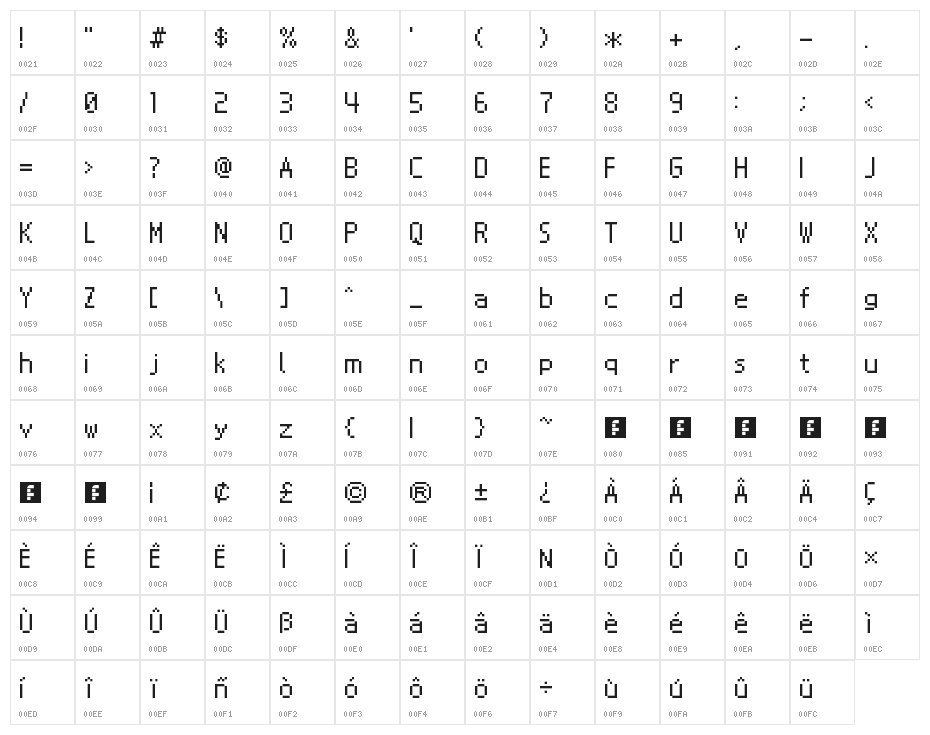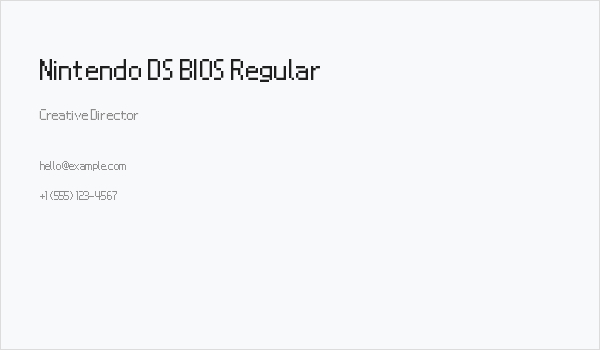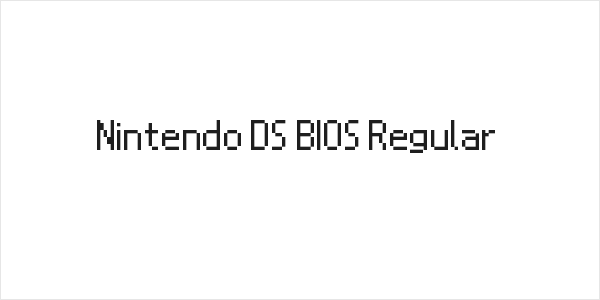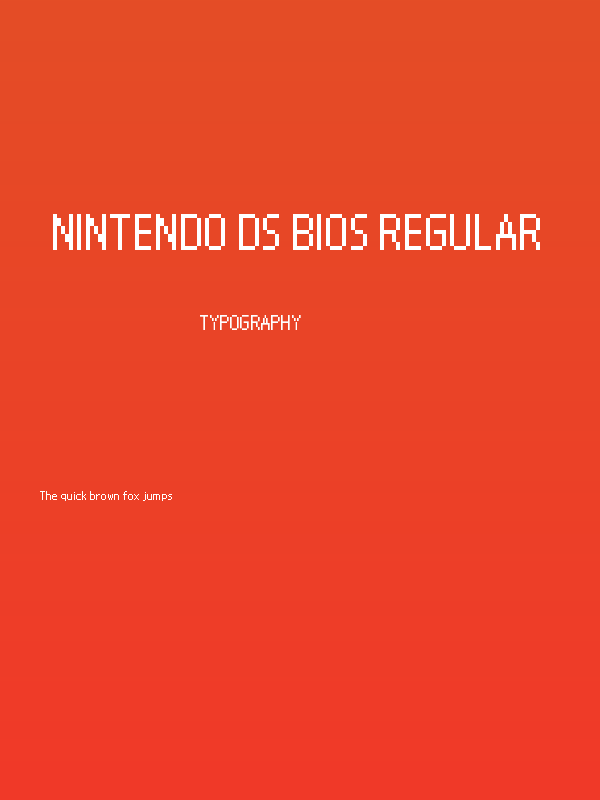
Nintendo DS BIOS Regular Font
✎ Pixel
| الفئات | Pixel |
| النمط العام | Retro, Digital |
| حالة الاستخدام | Digital displays, Coding, Retro designs |
| مشاريع مقترحة | Ideal for retro video game designs, digital displays, coding environments, and tech-themed graphics. |